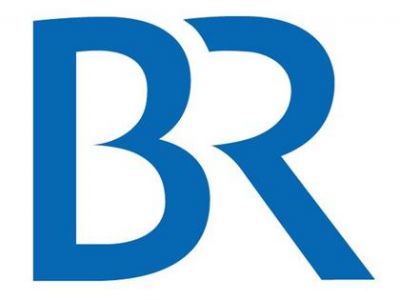
Die Bayerischen Rundfunkis
versuch doch einfach mal eine grotesk schrift zu nehmen und diese
proportionen nachzuvollziehen, vielleicht verstehst du es dann.
die formen können so einfach nicht stimmen.
die punze in dem R ist zu groß, zu schief und zu ungleich, wenn man
diese mit dem B vergleicht. dieses wiederum macht oben links einen
knick nach unten und auch die punze dort innen stimmt mit diesem
nicht überein, versuch mal die linien weiter zu zeichnen, in gedanken
zu verlängern etc. vielleicht wollte man auch eine ausgesparte 3 ereichen,
wer weiss. jedenfalls siehts schlimm aus. das R kippt, der diagonale strich
ist zu lang und sicher auch zu steil. es ist einfach nichts einheitlich,
nichtmal diese fiesen spitzen sind auf einer höhe.
wie ralf es schon sagte, besorg uns mal ne bessere version, dann können
wir dir die fehler anmalen. :roll:
Ich habe ein größeres Logo gefunden:
Mir ist zuerst der unharmonische Anschluss des Bogens unten am B aufgefallen (1.).
Auch wenn ich dieses auf-Details-rumreiten nicht mag, wenn das Gesamtergebnis an sich nicht schlüssig ist, hier ein paar Details:
- Die mittlere Horizontale (die Spitze) des B scheint genau die Höhe des Innenraumes zu halbieren (genaueres könnte ich mit einem PDF mit Vektoren sagen). Dadurch wirkt das B hängend, der obere Teil sollte weniger Platz beanspruchen wie der untere). Durch die Kurve die von oben recht steil zu der Spitze, und den flacheren Ansatz, der von der Spitze weg nach unten führt, wird diese Wirkung noch verstärkt.
- Die obere Punze des B hängt über (lehnt sich nach rechts), die untere hingegen tendiert nach links. Spitzenmäßige Dynamik...
- Das R braucht einen dickeren Fuß. Nicht viel, aber ein wenig. Wieviel müsste man ausprobieren.
- Das obere Ende des R, zum B hin, ist wabbelig, sowohl der Bogen an sich, als auch der rund angeschnittene "Puzzle"-Teil der sich ans B schmiegen soll.
- Diese beiden Spitzen: Wie kommt man auf die Idee, ein Logo das vornehmlich im Fernsehen gezeigt wird, mit solch einem Detail auszustatten, während man sonst eine relativ robuste Linienführung wählt? Zumindest anschneiden hätte man sie müssen, um nicht dem Fernseher die totale Freiheit zu lassen, welche Details er noch anzeigt und welche nicht mehr.
- noch mehr?
Man schaue sich doch nur mal die drei Punzen an und vergleicht diese Weißräume.
Also ich hoffe, jetzt fällt jedem Kritiker der Kritiker auf, dass es sich hierbei um eine
handwerklich schlechte Arbeit handelt und diese Punzen absolut ungleichmäßig
und eierig wirken.
Ich finde es auch heikel, fremde Logo-Kreationen zu kritisieren – zumal man ja nicht alle Gedankengänge nachvollziehen kann und wahrscheinlich auch zu einem ganz anderen Ergebnis gekommen wäre. Ich finde es aber auch ganz gut sich mit solch einem Logo im Detail zu beschäftigen. Ich bin kein Schriftzeichner, finde aber – mal allgemein gesprochen, dass das Logo hier und da »eiert«. Robertmichael, Sebastian Nagel und Ralf Herrmann haben das meiner Meinung nach schon sehr gut auf den Punkt gebracht.
Und weil es Spass macht, habe ich mal ein paar der Stellen eingekreist, über die ich persönlich nochmal drüber gegangen wäre. :)
Ich finde es gar nicht heikel. Denn ein Logo soll ja gerade aus dem Stand heraus wirken und nicht erst erklärt werden müssen. Auf mich, der sich mit Bezierkurven höchstens als Bestandteil einer Illustration beschäftigt, wirkte das Logo von Anfang an schief und irgendwie unsauber. Briefing hin oder her. Und der BR zahlt gut, das kann ich aus eigener Erfahrung bestätigen, dafür sollte man was verlangen dürfen, das gerade den Schriftlaien überzeugt ...
Traut Ihr Euch?
Schickt doch den Link zu Eurer Diskussion hier an Mercedes Riederer vom BR:
Sie war in den 1990er Jahren lange Zeit Stellvertretende Leiterin der DJS (Deutsche Journalisten-Schule) in München. Die bekamen damals, gesponsort von der Süddeutschen Zeitung, ein Atex-System. Und ich habe das System damals installiert und vier Wochen Schulung gegeben. Wer sie kontaktiert, soll sie bitte von mir grüßen. Ich bin ganz sicher, daß sie sich erinnert.
Sie ist eine sehr patente Person, völlig offen für kritische Diskussionen und ich könnte mir vorstellen, daß sie Euch einen der verantwortlichen für diesen Entwurf als Diskussionspartner hierher vermittelt.
Na los... macht schon.
Mit aller Wertschätzung: So eine Alleinkritik wäre doch viel fruchtbarer, wenn ein Entscheider dabei wäre.
Frau Riederer ist leider die falsche Adresse, Georg. Sowas wird nicht von den Journalisten entschieden. Auch nicht von den Besten.
So ähnlich.
Ausserdem kenne ich jemanden, der in einer anderen Agentur daran gearbeitet hat.
Ich hatte schon damals überlegt, ob das ganze nicht nur ein Entwurf ist, der etwas verfrüht an die Öffentlichkeit getragen wurde. Das würde die lausige Umsetzung erklären und auch, dass das Logo sonst noch nicht gesichtet wurde. :?
das habe ich mir auch schon gedacht. bis heute ist mir das logo noch
nirgendwo aufgefallen. vielleicht haben sie es auch wegen der schlechten
kritik zurückgenommen.